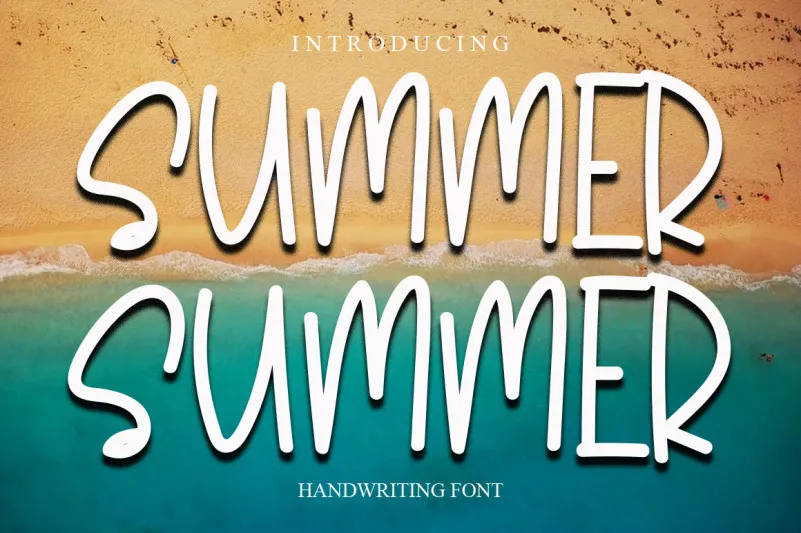
A fonte ‘Summer Summer’ é uma paixante original e amigável, perfeita para aqueles que querem adicionar um toque especial a suas postagens no Instagram ou projetos DIY de escrita à mão livre. Seja você criando um feed colorido para sua conta da rede social, criando um cartão de aniversário personalizado ou até mesmo decorando seus lares com uma arte texturizada única e moderna, esta fonte irá tornar qualquer ideia artística em algo verdadeiramente inovador e lindo. Seja qual for a sua necessidade gráfica, Summer Summer oferece um design único capaz de criar trabalho de arte perfeito.